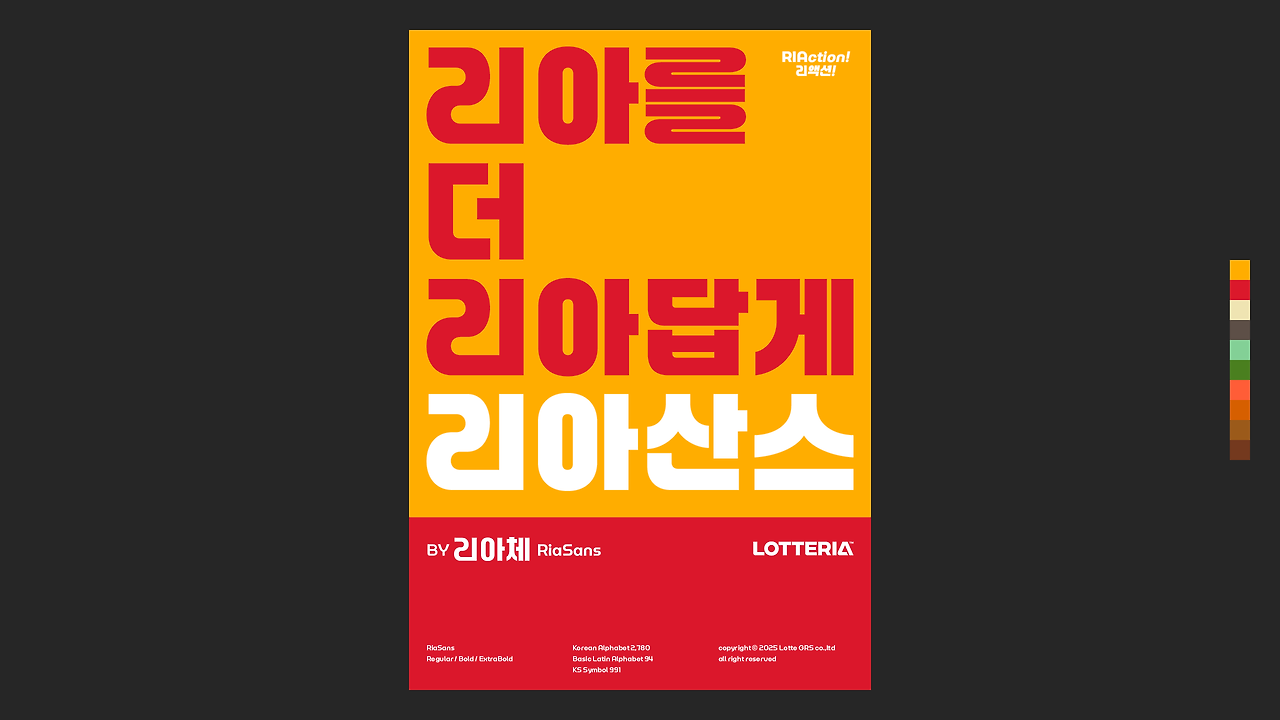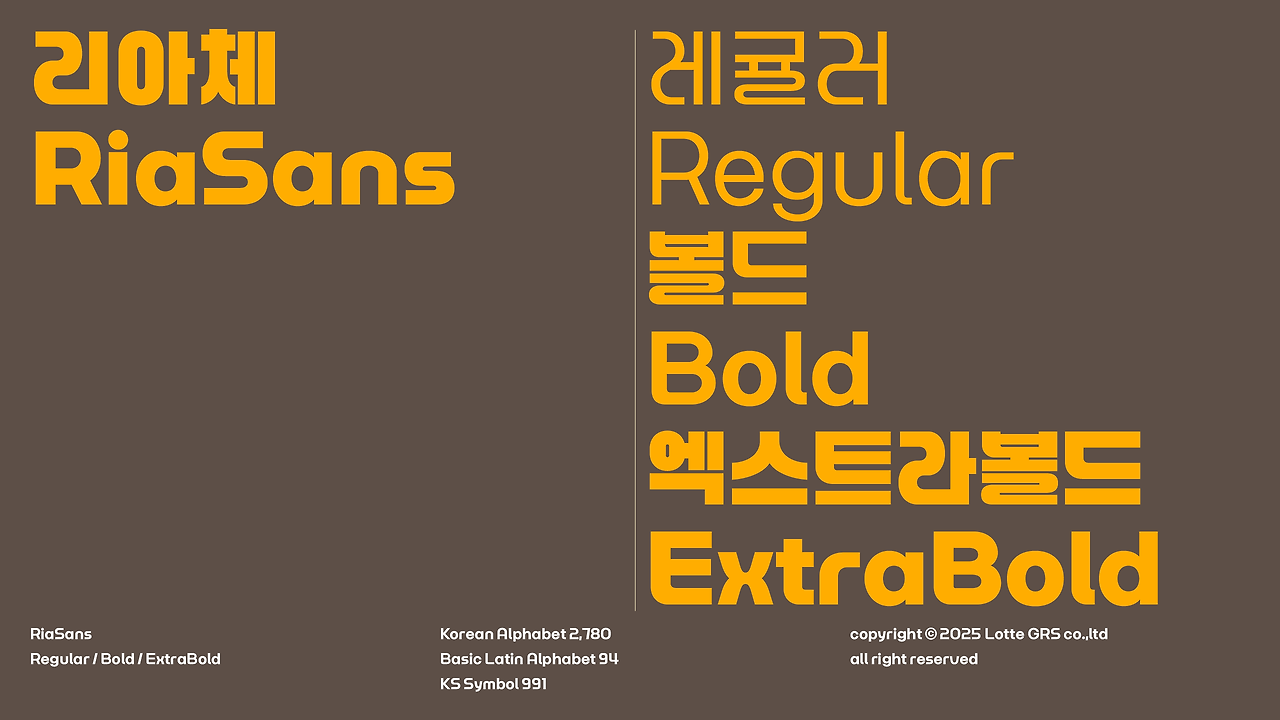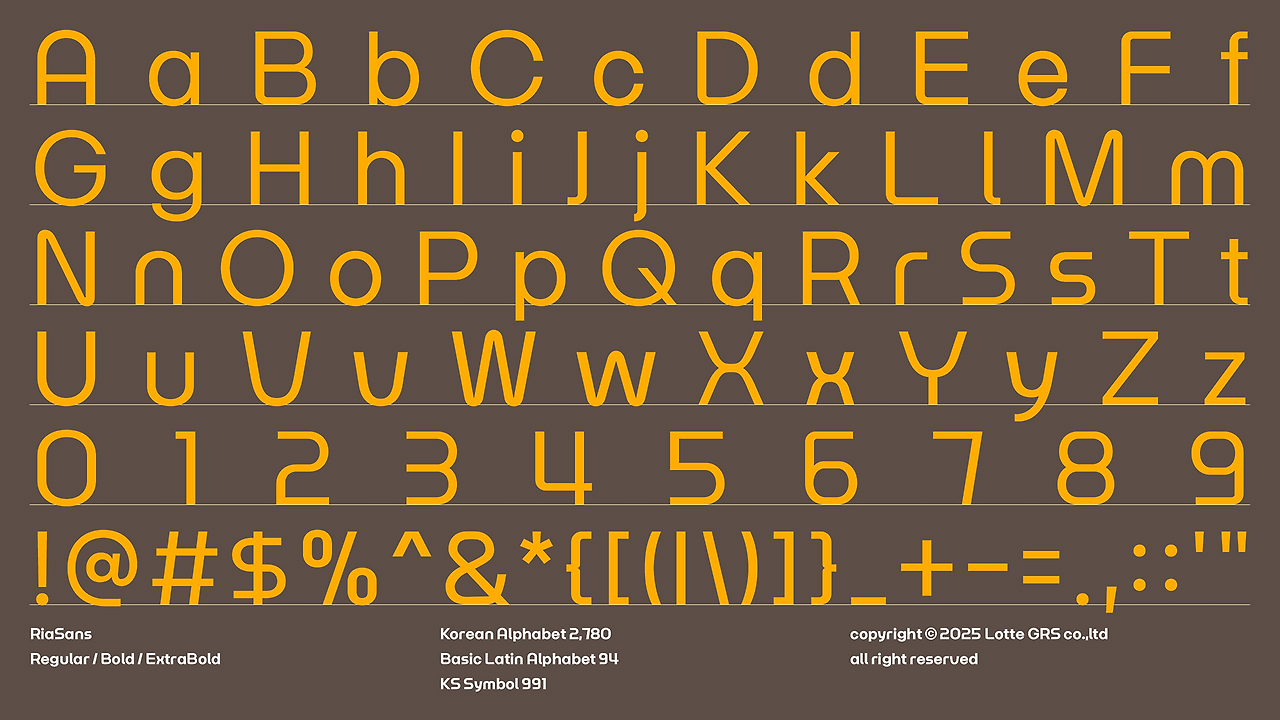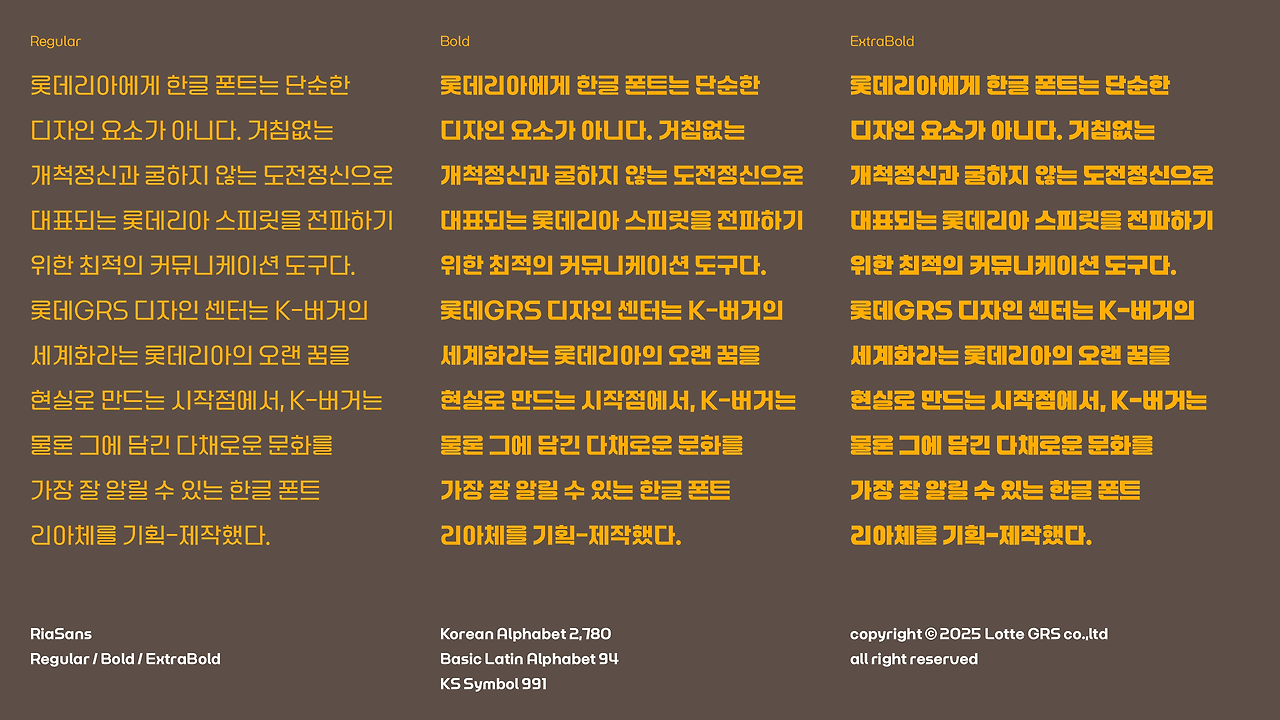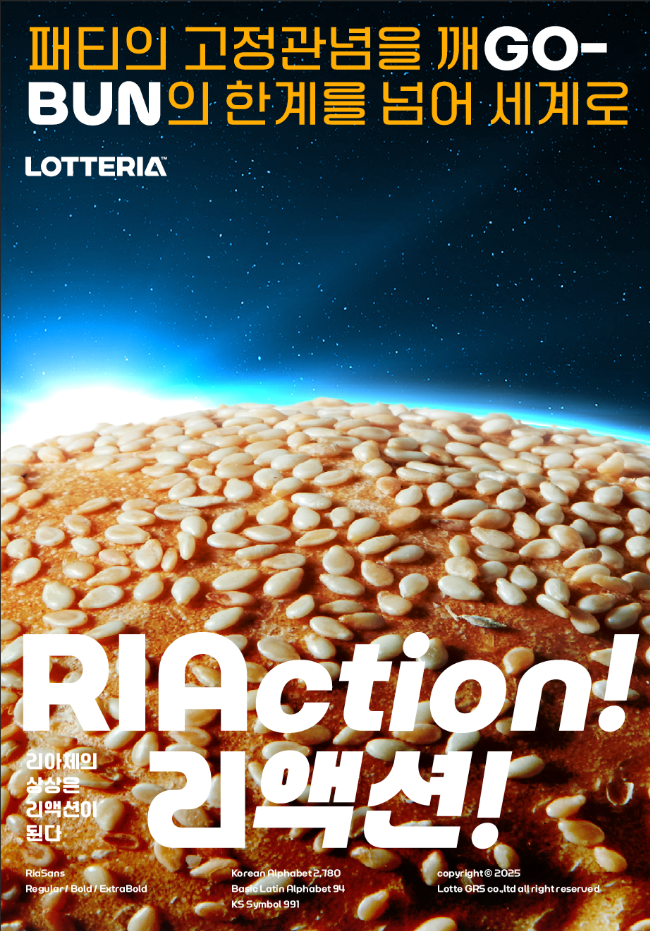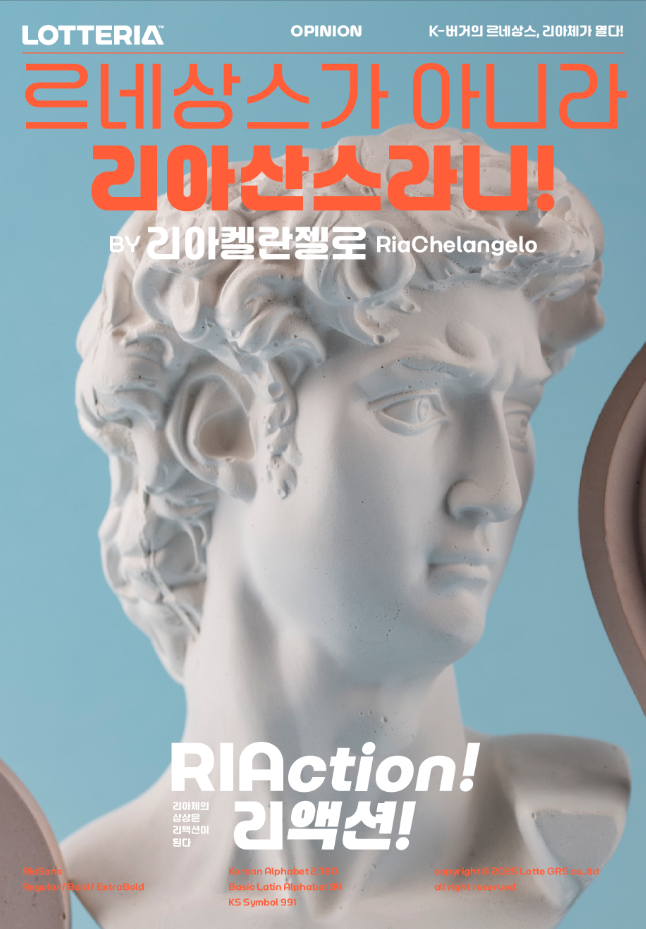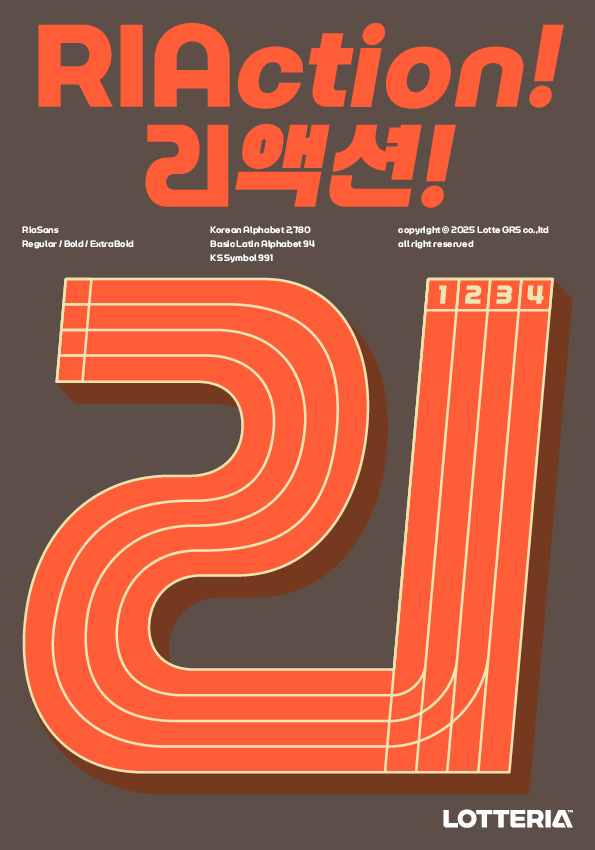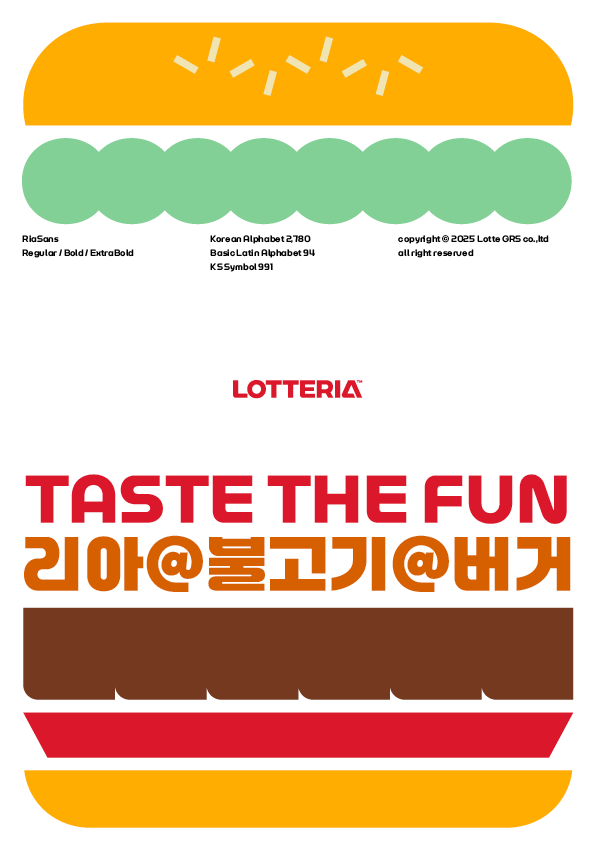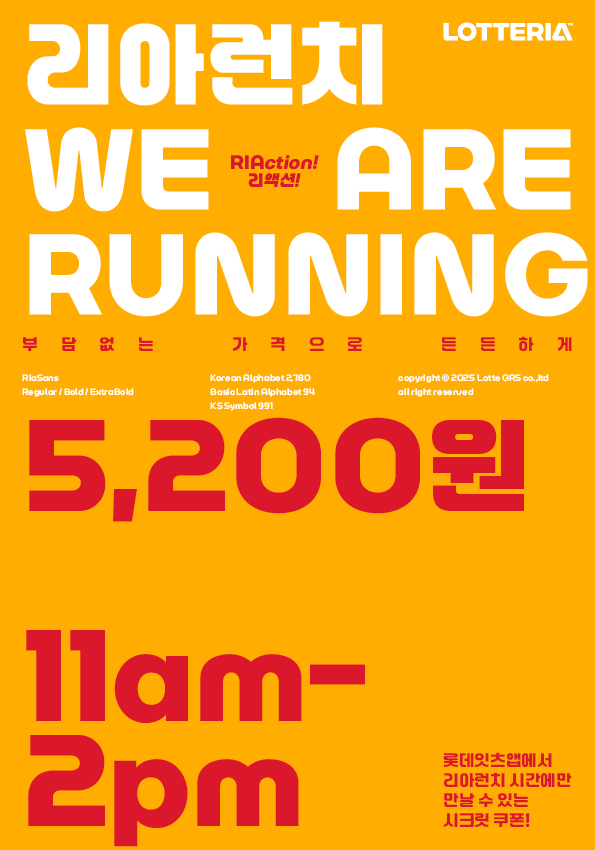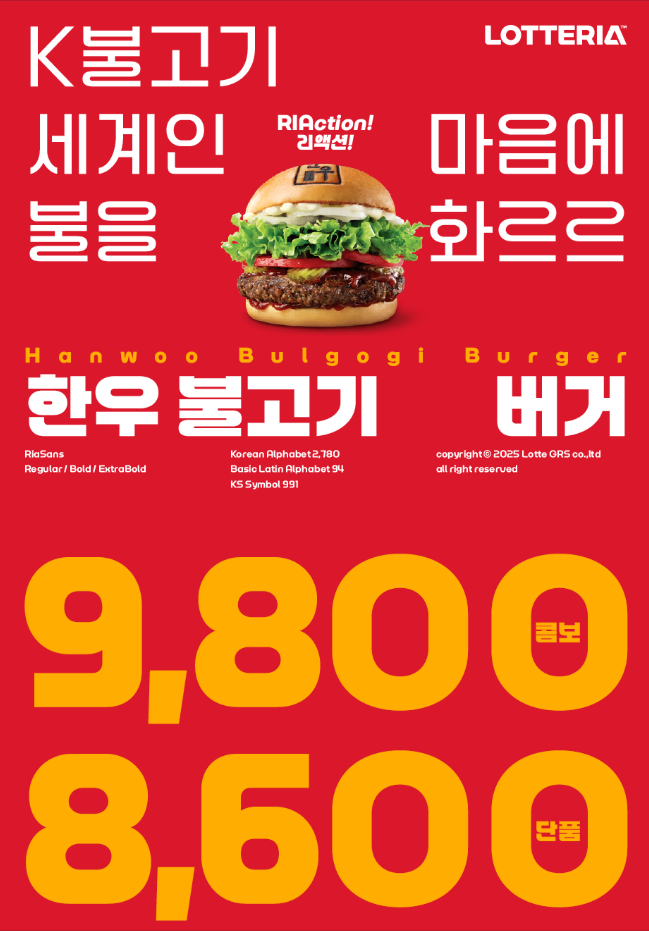
롯데리아가 브랜드의 정체성과 감성을 담아 직접 전용 서체 "리아체(RiaSans)"를 선보였습니다. 리아체는 브랜드 고유의 이미지를 글자 하나하나에 담아낸 서체로, 광고, 포스터, 패키지 등 다양한 매체에 활용될 수 있도록 기획되었습니다. 특히 최근 MZ세대와의 소통을 강화하고 있는 롯데리아가 단순한 제품 홍보를 넘어 '브랜드 경험'의 일환으로 폰트까지 직접 제작했다는 점에서 주목받고 있습니다.
롯데리아 폰트 리아체, 리아 액션 스타트!
국민 버거는 국민 폰트로 알려야 제맛! 리아를 더 리아답게 만드는 가장 리아다운 폰트, 리아체가 세상의 중심에서 K-버거를 이야기합니다
✍️ 리아체의 디자인 특징 – "맛있는 감성, 부드러운 곡선"
리아체는 손글씨의 따뜻함을 기반으로 디자인된 부드러운 곡선과 리듬감 있는 획이 특징입니다. 자소 간의 간격을 적절히 조정하여 가독성을 높였고, 각 글자의 형태는 맛있는 식품 이미지를 떠올릴 수 있도록 친근하게 구성되었습니다. 일반적인 고딕체나 명조체와는 다른 감성 서체로, 브랜드에 감성적이고 트렌디한 분위기를 부여하고자 할 때 효과적입니다.
📦 활용 범위 – 매장부터 콘텐츠까지, 전방위 확장
리아체는 롯데리아의 매장 내부 디스플레이, 메뉴판, 포장지 디자인, SNS 콘텐츠 등 다양한 채널에서 사용되고 있으며, 향후 더 넓은 브랜드 캠페인에도 적용될 예정입니다. 일부 콘텐츠에서는 소비자와의 공감형 메시지를 전달하는 데 사용되고, 타이포그래피 자체가 마케팅 도구를 활용되는 트렌드를 잘 보여주고 있습니다. 기업의 브랜드 커뮤니케이션 전략에 있어 전용서체는 이제 필수적인 자산으로 자리 잡아가고 있습니다.
🧱 제작 배경 – "브랜드의 언어를 시각화하다"
롯데이라는 리아체 개발을 통해 "롯데리아만의 목소리와 톤앤매너를 글자에 담고 싶었다"는 철학을 실현하고자 했습니다. 브랜드가 직접 서체를 개발하는 트렌드는 글로벌 기업들 사이에서도 점차 확산되고 있으며, 이는 브랜드 경험(Brand Experience) 시대에 있어 서체 역시 하나의 브랜딩 요소로 가능하기 때문입니다. 롯데리아는 이번 서체 개발을 통해 브랜드 아이덴티티를 보다 일관되고 감성적으로 소비자에게 전달할 수 있게 되었습니다.